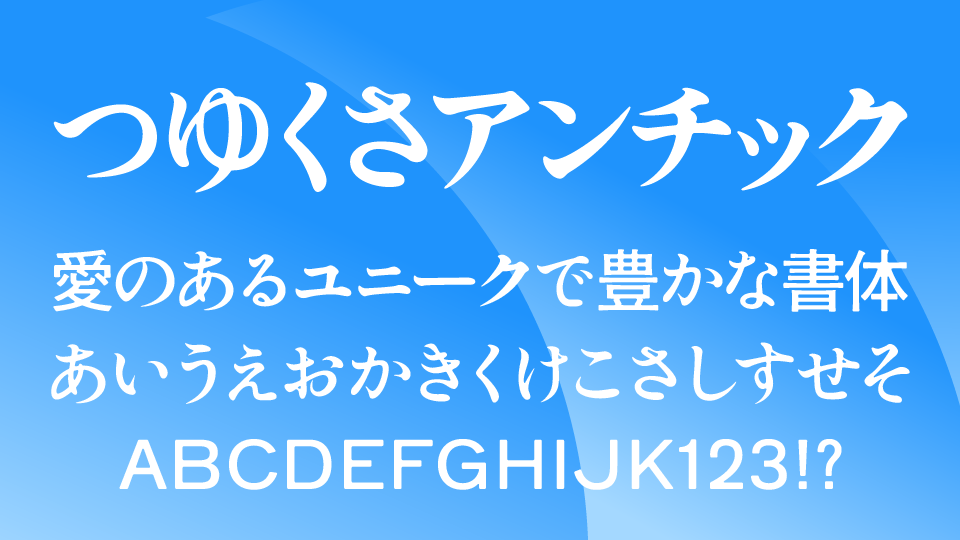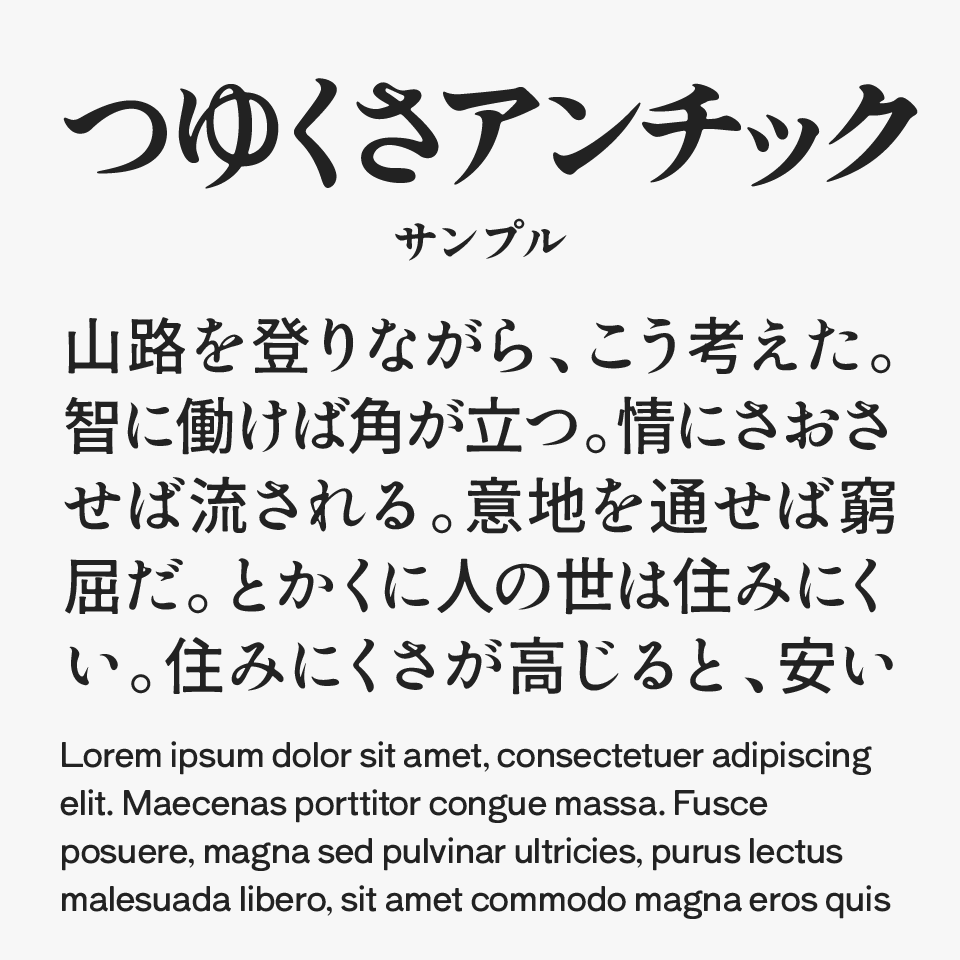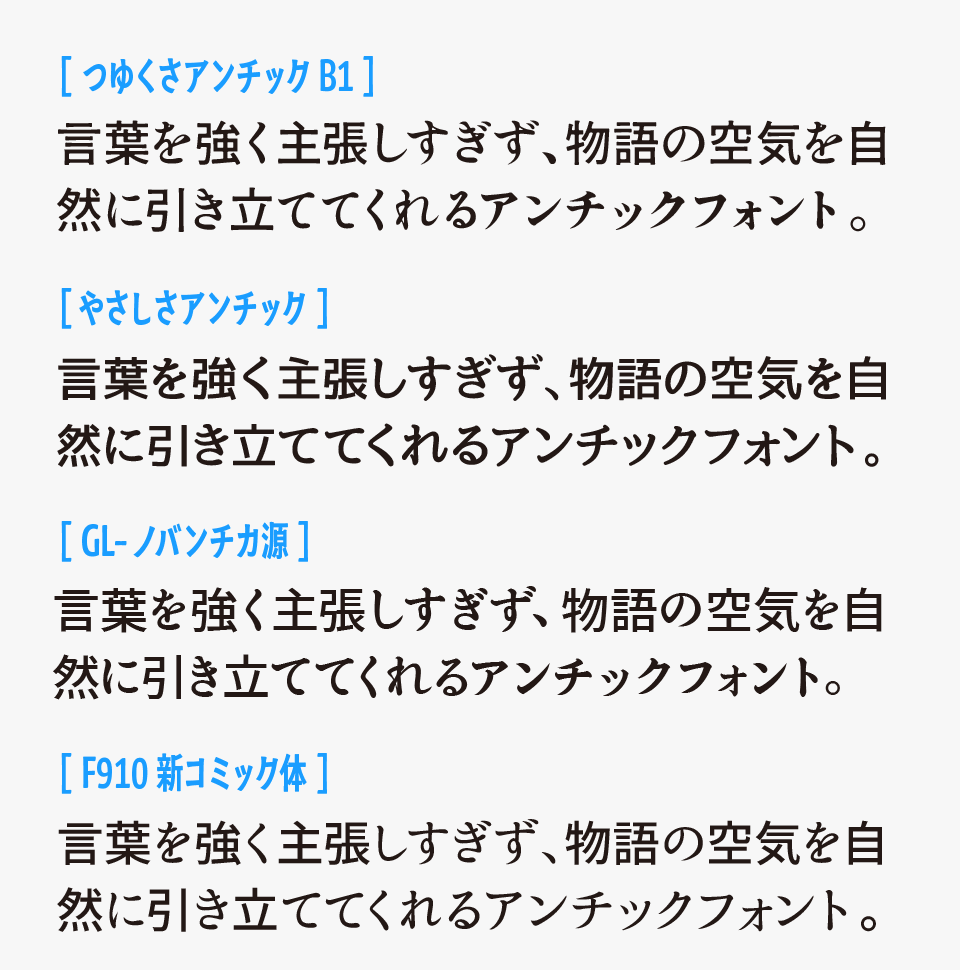
つゆくさアンチックは、「しっぽりアンチック」フォントをベースに調整されたアンチックフォントです。
同封されているつゆくさアンチックB1には、ボケ足が追加されており、墨溜まりのような質感が感じられるフォントとなっています。
流れるような曲線と柔らかな抑揚が美しく、文字全体から文学的で落ち着いた空気が漂います。古い書籍や文芸誌を思わせる趣がありながら、重たくなりすぎない軽やかさも感じられるフォントです。
マンガの吹き出し文字はもちろん、小説の表紙や詩集、和風デザイン、レトロな読み物系コンテンツなどと相性が良いフォントです。
つゆくさアンチック
つゆくさアンチックをほかのアンチックフォントと比較してみると、やわらかく上品な雰囲気が特に印象的です。
比較フォントは、「やさしさアンチック」「GL-ノバンチカ源」「新コミック体」と使用していますが、同じアンチック体でも雰囲気がガラっと違いがありどれもステキなので、ぜひあわせてチェックしてみてください。
つゆくさアンチックと、「やさしさアンチック」「GL-ノバンチカ源」「新コミック体」フォントを比較